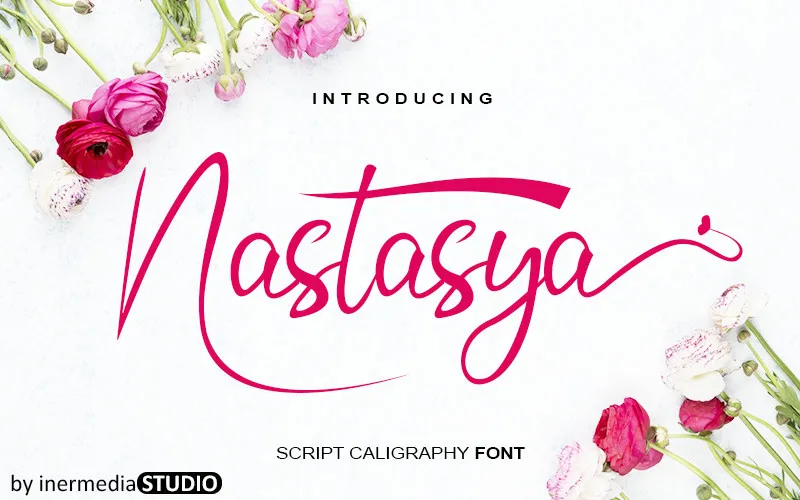
A Nastasya Script Font é uma elegante tipografia feita à mão, cheia de suaves detalhes e ligaturas que tornam essa fonte extremamente versátil. Com seus deliciosos traços curvos e delicadas pontas finas, você pode transformar qualquer ideia criativa em verdadeiros trabalhos de arte, sejam eles para o Instagram ou projetos de calligrafia DIY. Esta fonte é perfeita para quem busca uma mão feminina e amigável que se adequa a diversos estilos, desde os mais elegantes até as formas mais descontraídas. Nastasya oferece um toque único à sua marca, tornando-a ainda mais única e especial em qualquer mídia onde ela é usada. Seja para uma pequena etiqueta de presente ou o cartão da sua empresa, a Nastasya Script é a escolha certa para quem busca algo bonito e autêntico.